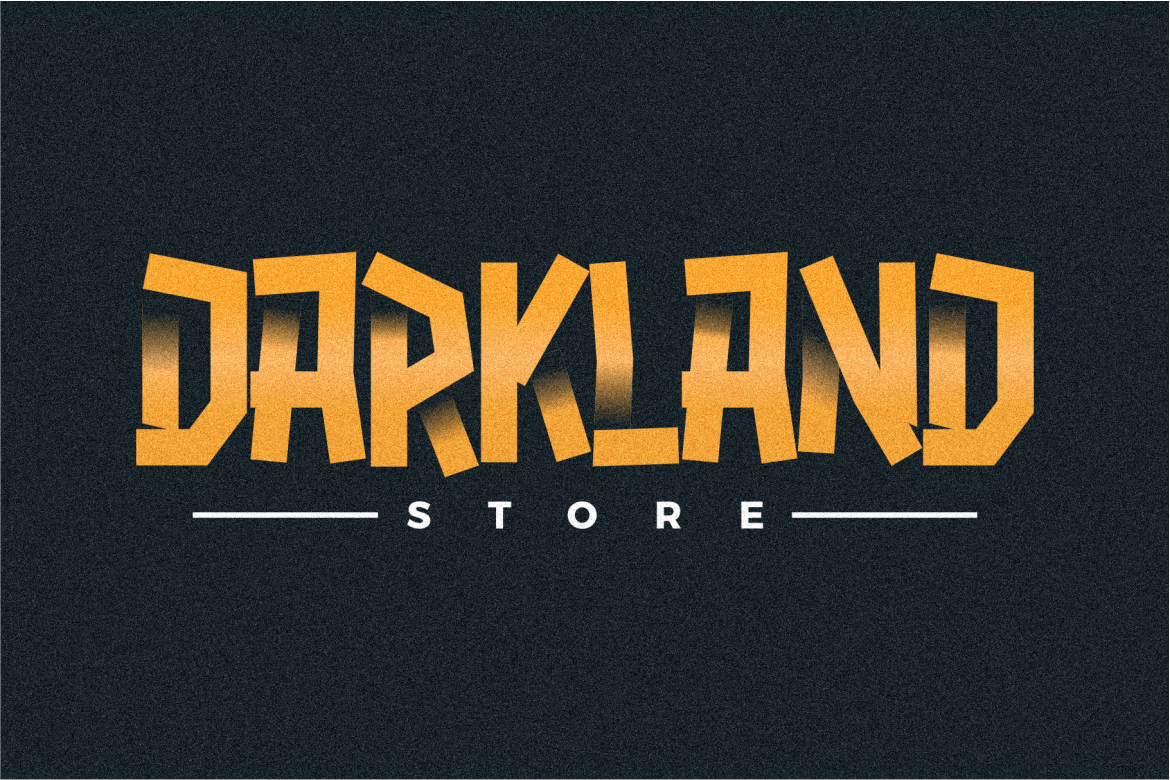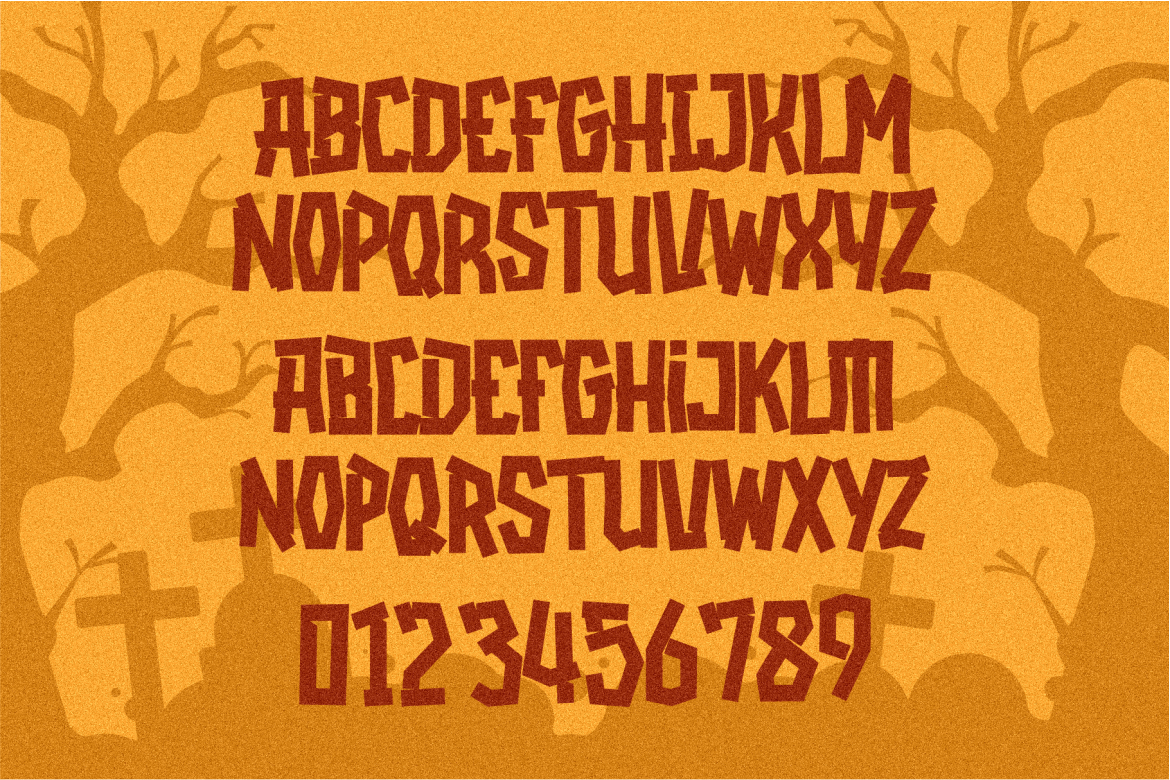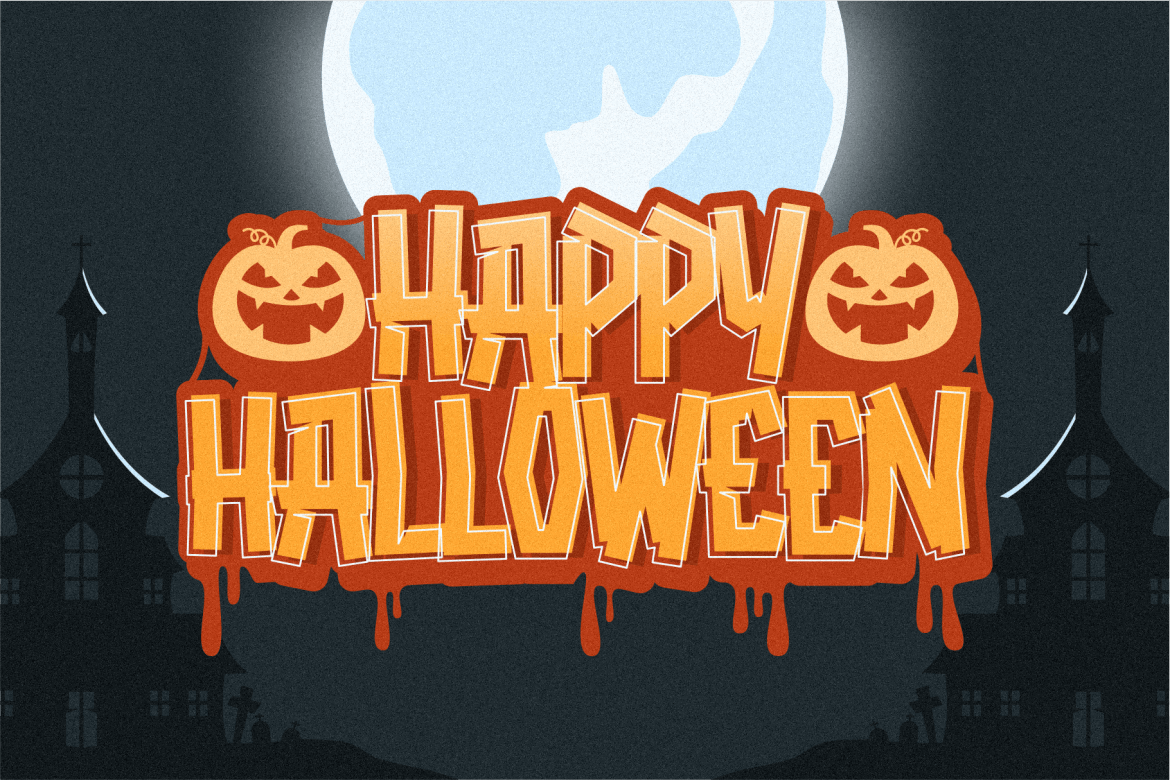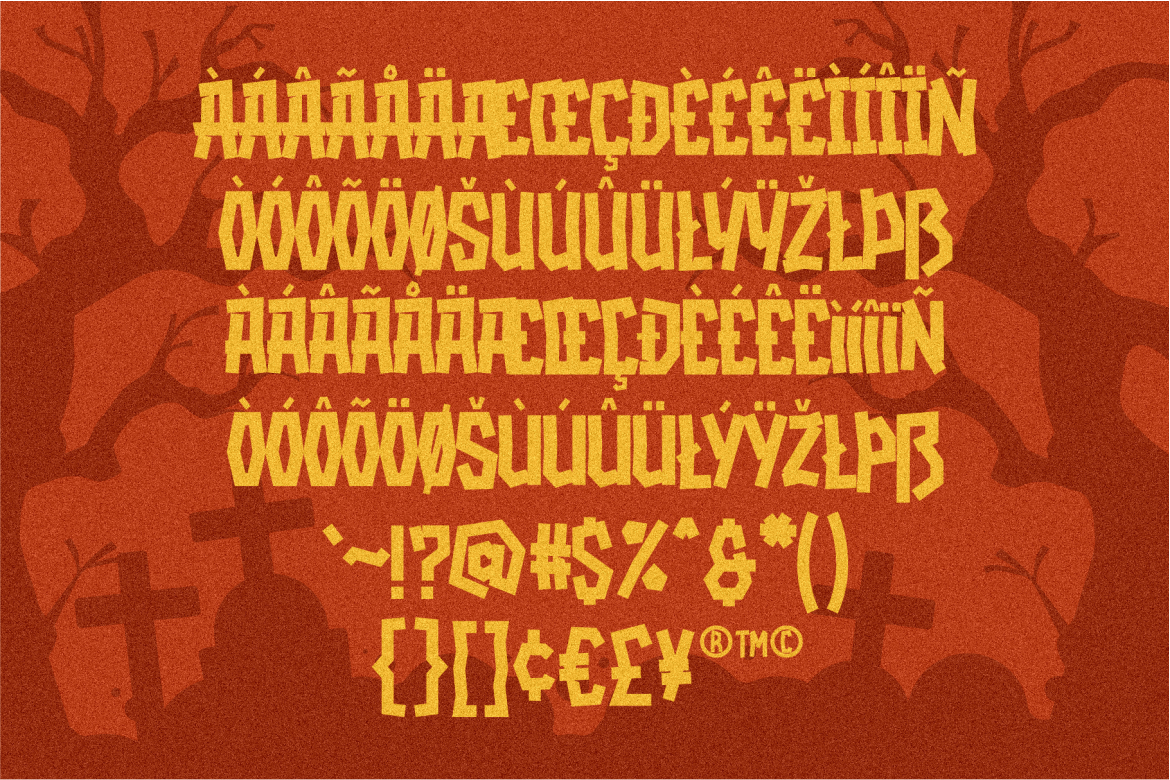
دانلود فونت انگلیسی Grivint Typeface
GRIVINT یک فونت مردانه مناسب برای طراحی های مربوط به موسیقی ، گروههای موسیقی ، لباس ، پوستر ترسناک ، خطوط لباس یا موارد دیگر است ، می تواند به عنوان پوستر ، کارت پستال ، آرم و غیره استفاده شود.